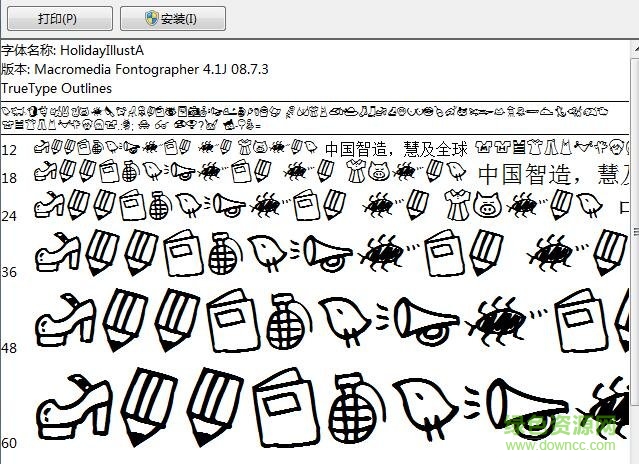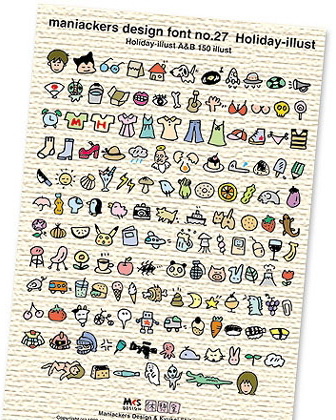
可愛卡通涂鴉字體可以在大多數(shù)計(jì)算機(jī)操作系統(tǒng)上安裝使用,這類字體看起來像涂鴉效果一樣生動(dòng)??梢杂脕碓O(shè)計(jì)一些兒童類海報(bào)、。宣傳冊等等。喜歡的用戶快來綠色資源網(wǎng)下載使用吧。
可愛卡通涂鴉字體是一款圖案字體,集卡通和涂鴉元素于一體,字體比較可愛,極富兒童風(fēng)格,適合在兒童節(jié)使用。直接將。ttf格式文件復(fù)制到C:\WINDOWS\Fonts目錄下即可。